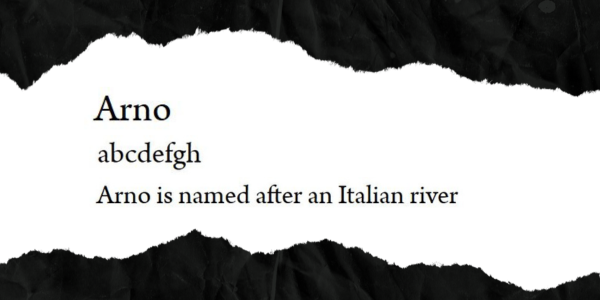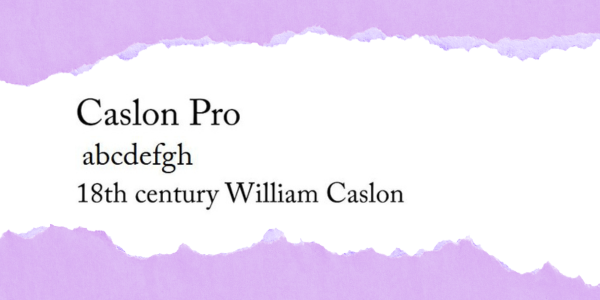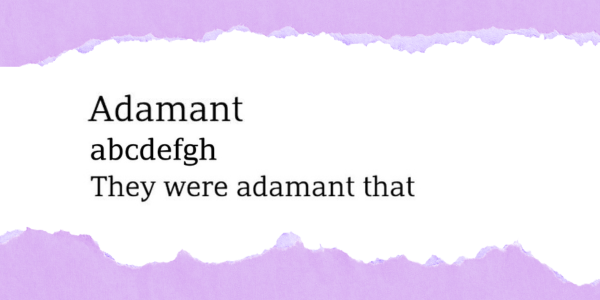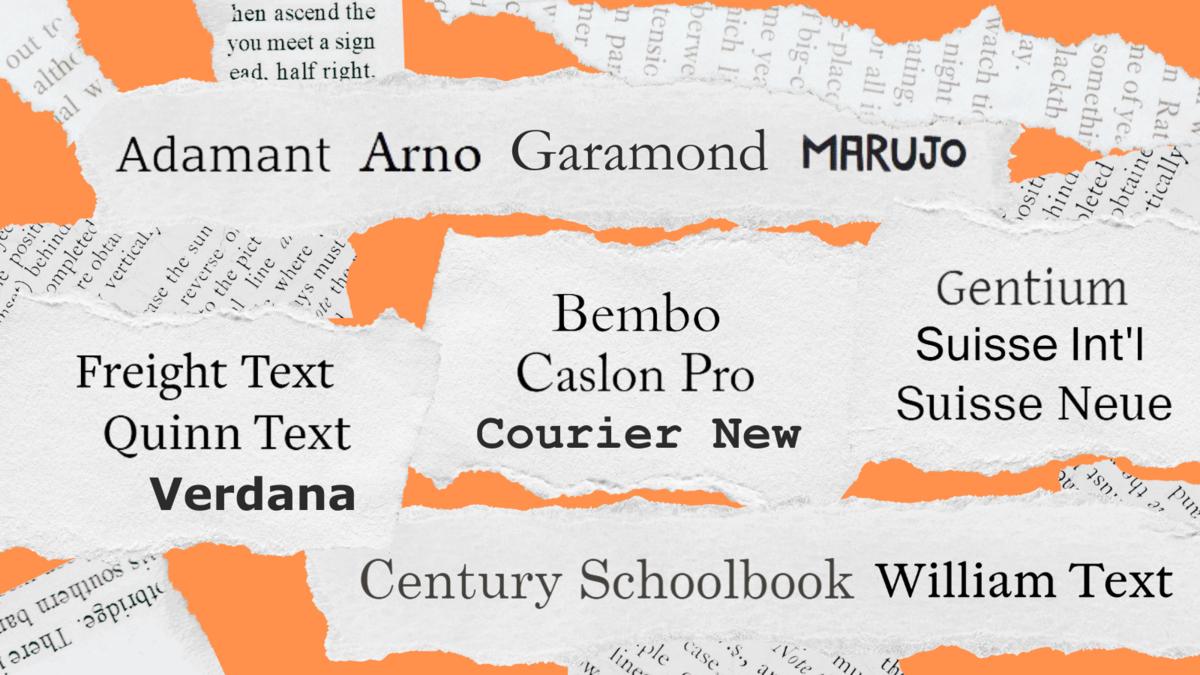
В мире шрифтов: как выбрать идеальный для книг?
Эй, привет! 🤗 Давайте поговорим о шрифтах. Что мы знаем о шрифтах, кроме того, что они бывают разные и кажутся иногда довольно скучными? Как ни странно, но выбор шрифта может стать настоящим искусством. Особенно когда речь идет о книжном дизайне.
Ведь хороший шрифт — это не только умение создавать красоту, но и функциональность. Читаешь ты книгу, а там такие буквы, что можно и глаз не открыть. 😵💫
Так о чем же нам нужно задуматься, выбирая шрифт для книги? Давайте углубимся в эту тему!
Читабельность на первом месте
Вы задумывались, почему одни книги читаются, как горячие пирожки, а другие заставляют вас зевать уже с первой страницы? Все дело в читаемости! Многие факторы влияют на то, как легко читателю воспринимать содержание текста: размер, форма букв, расстояние между ними и даже их стиль.
Представьте, что вы читаете мангу с мелким текстом. Это же пытка! 🤬 Поэтому так важно знать, какие шрифты подходят для какого типа текста. Погнали разбирать несколько суперкрутых шрифтов, которые цементируют свои позиции на книжном рынке уже достаточно долго!
Топ-5 шрифтов для книг
Adamant
Этот шрифт просто шикарен для книг! ✅ Он читается даже в малых размерах, то есть для тех, кто обожает держать книгу в руках и при этом не моргать. Шесть различных весов делают его универсальным. Широкие апертуры — это его фишка, благодаря которой текст просто «течёт» и не вызывает напряжения!
Arno
Этот классический шрифт – настоящая находка для многоязычных книг. Его универсальный дизайн не оставляет шансов нежелательной читаемости!
Bembo
О, этот красавец был создан ещё в 1920-х годах, но до сих пор находится на пике популярности благодаря своим серефам и, конечно же, хорошей читаемости. Вот это да!
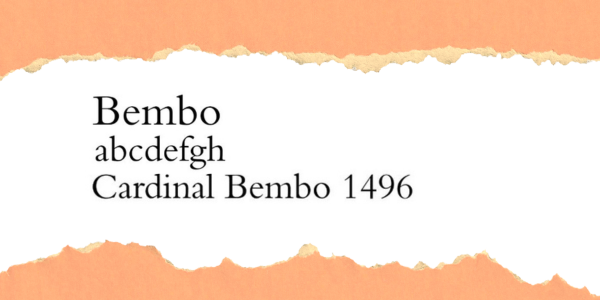
Caslon Pro
Возвращение в 18 век? Без проблем! Этот шрифт по-прежнему удерживает свои позиции и очень крут для печати. Если вы хотите сделать атмосферу старины и классики, он точно вам в помощь!
Century Schoolbook
Всем новичкам – этот шрифт! 🐣 Он снискал популярность среди учебников в Америке благодаря округлым формам, которые визуально облегчают восприятие. Просто класс!
В итоге
Каждый из этих шрифтов обладает своей уникальной магией, способной сделать чтение не только увлекательным, но и комфортным. 🤓 Подбирайте шрифты под жанр и целевую аудиторию, и убедитесь, что они не только красивы, но и удобны. Ведь кто хочет мучиться, читая книгу?
Таким образом, выбор шрифта – это как выбор настроения для книги. Убедитесь, что он передает ту атмосферу и эмоции, которые вы хотите донести до своего читателя!